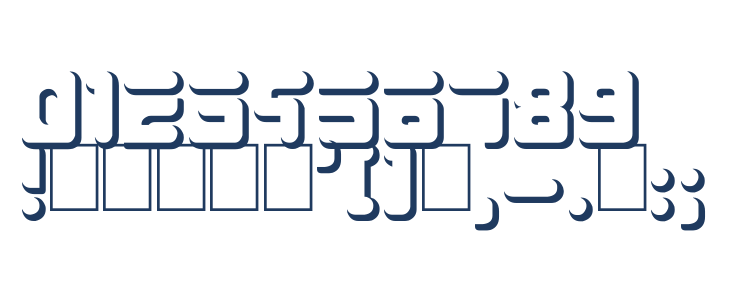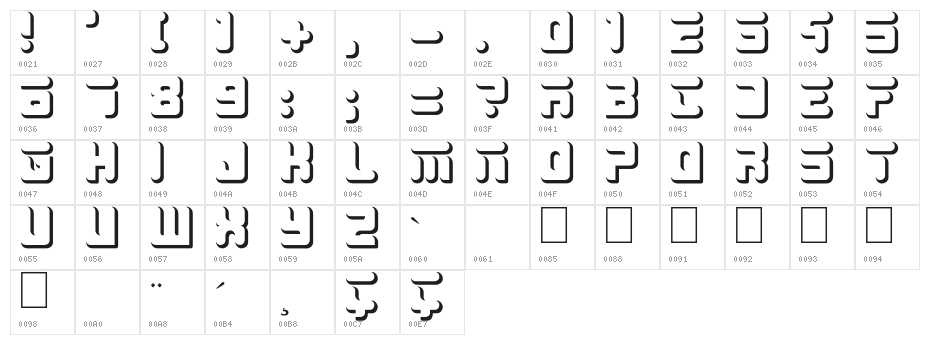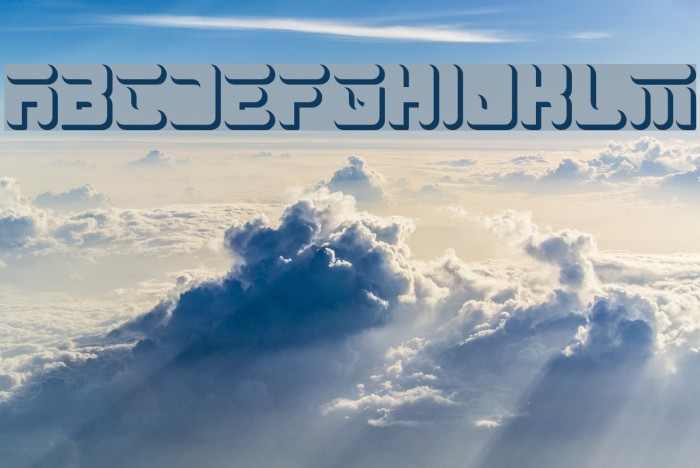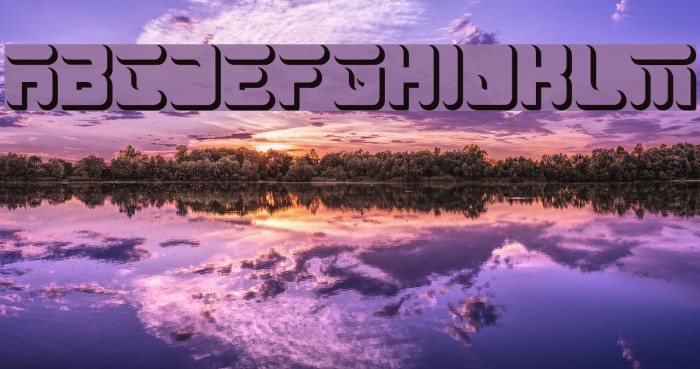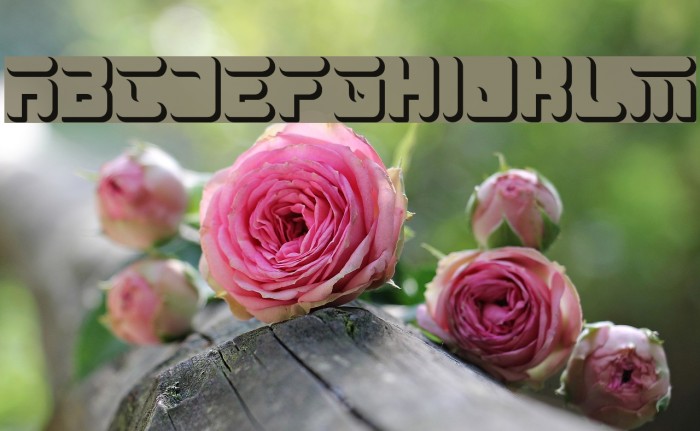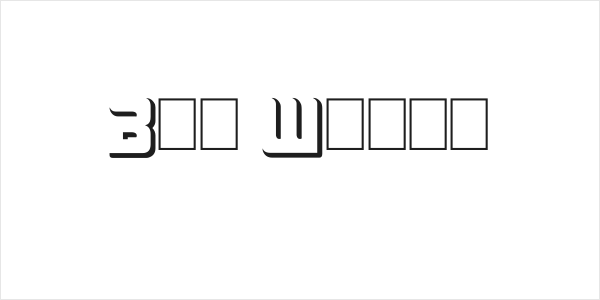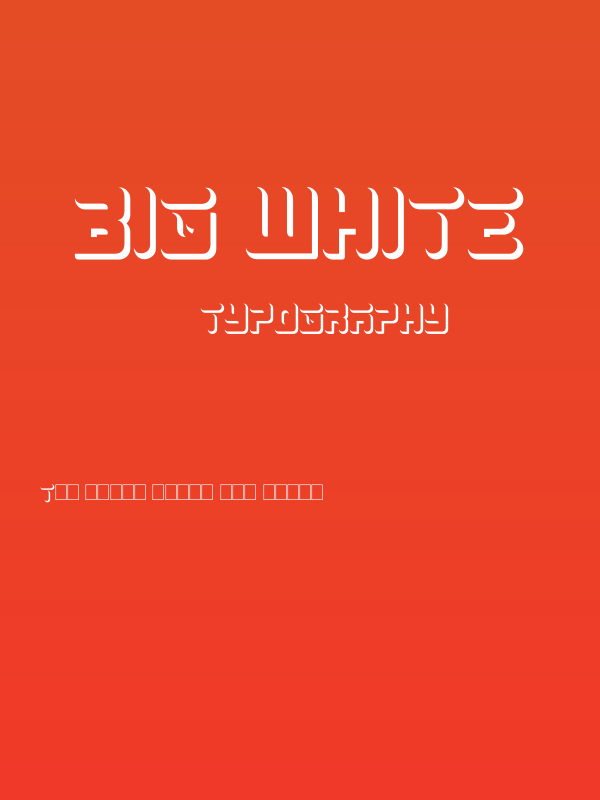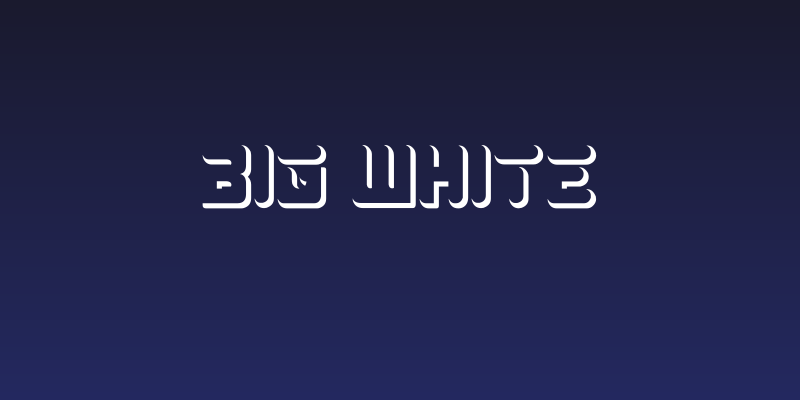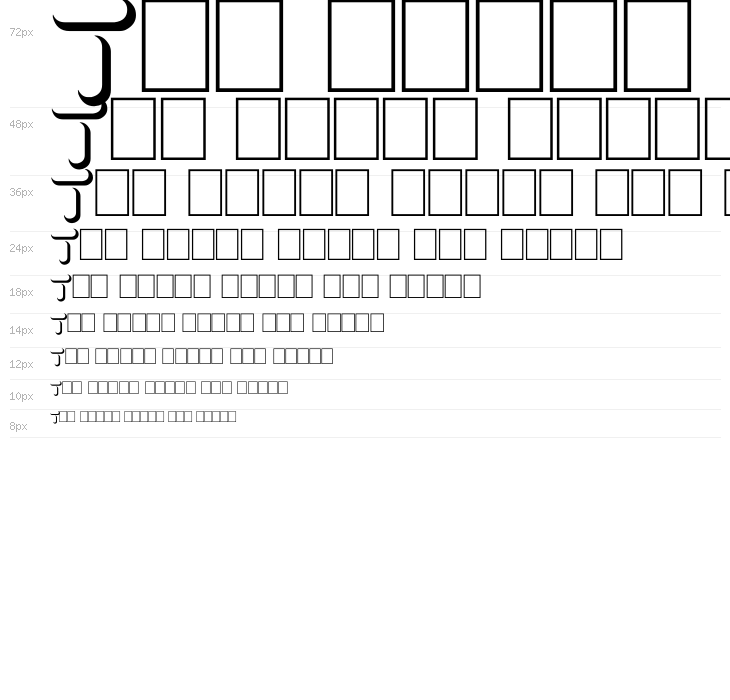
Big White Font
| Proiecte propuse | Ideal for sci-fi themed projects, video game titles, posters, and branding that requires a modern, eye-catching typeface. |